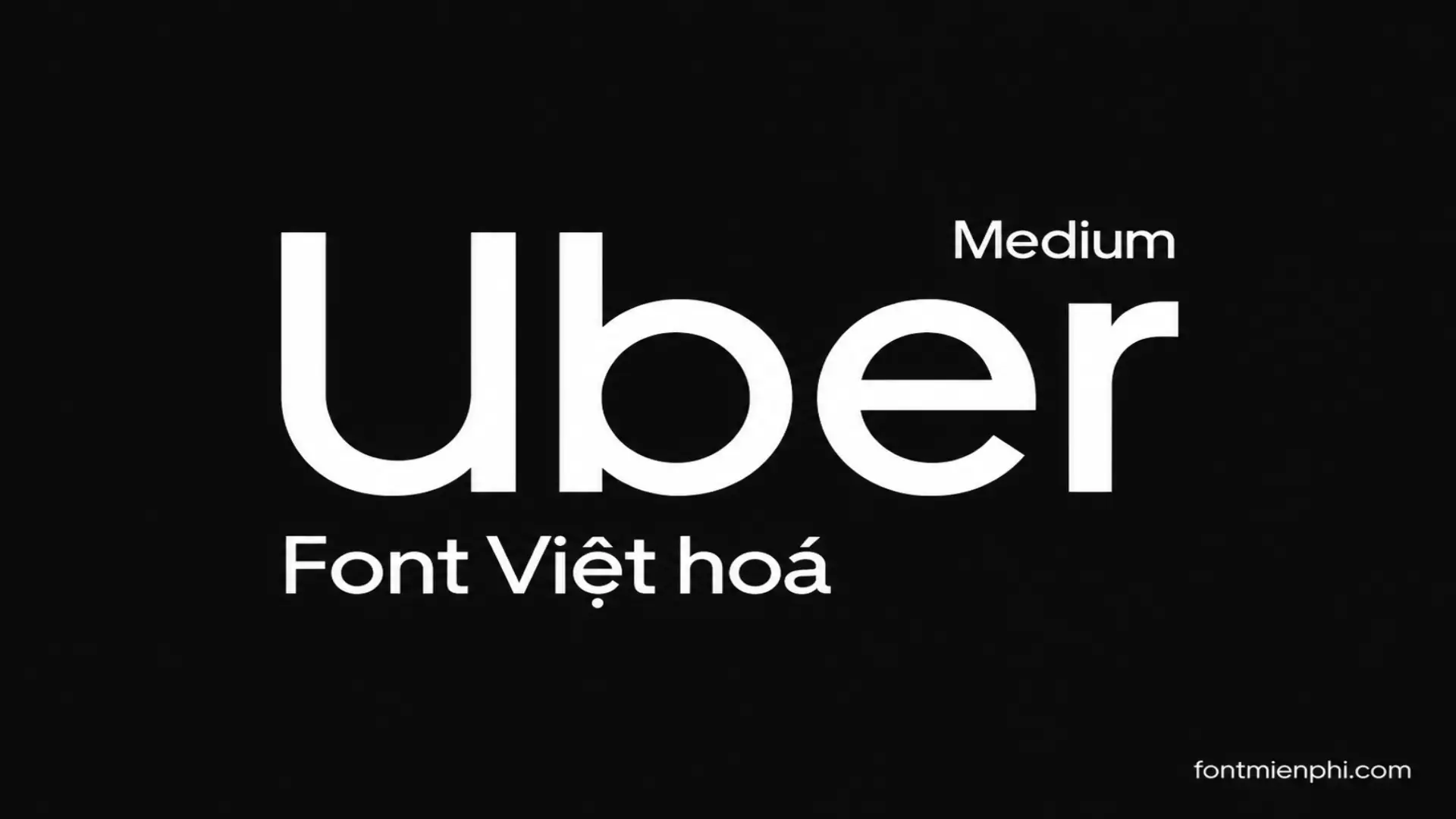
Tải Font Việt Hóa 1FTV VIP Uber Move Medium – Phông Chữ Hiện Đại, Chuyên Nghiệp
Nếu bạn đang tìm kiếm một phông chữ mang hơi thở đương đại, vừa tinh tế, sang trọng lại vô cùng chuyên nghiệp, thì Font Việt hóa 1FTV VIP Uber Move Medium chính là sự lựa chọn không thể bỏ qua. Đây hiện đang là một trong những phiên bản font chữ được cộng đồng Designer ưa chuộng nhất cho các dự án yêu cầu tính thẩm mỹ cao.
1. Giới thiệu về Font Việt hóa 1FTV VIP Uber Move Medium
Được phát triển dựa trên bộ phông chữ gốc đình đám của thương hiệu gọi xe công nghệ toàn cầu Uber, 1FTV VIP Uber Move Medium kế thừa trọn vẹn tinh thần cốt lõi: tối giản, hiện đại và hướng tới người dùng.
Phiên bản có độ dày Medium (trung bình) mang lại sự cân bằng hoàn hảo – không quá thanh mảnh gây khó nhìn, cũng không quá dày đặc gây cảm giác nặng nề. Đặc biệt, bản Việt hóa từ đội ngũ 1FTV đã được xử lý kỹ thuật tỉ mỉ, giúp các dấu câu tiếng Việt hiển thị mượt mà, đảm bảo sự rõ ràng và dễ đọc tuyệt đối trên mọi nền tảng.
2. Đặc điểm nổi bật của bộ Font 1FTV VIP Uber Move Medium
Phông chữ này mang trong mình những đặc tính xuất sắc để chinh phục mọi nhà thiết kế khó tính nhất:
Thiết kế tinh tế & chuyên nghiệp: Các đường nét được thiết kế bo góc nhẹ nhàng nhưng vẫn giữ được form dáng cứng cáp, mang lại cảm giác chỉn chu, đáng tin cậy.
Phong cách sang trọng & hiện đại: Rất phù hợp với xu hướng thiết kế tối giản (Minimalism) đang lên ngôi trong những năm gần đây.
Tối ưu hóa trải nghiệm đọc: Không gian giữa các chữ cái (kerning) được tính toán chuẩn xác, giúp người dùng dễ dàng tiếp nhận thông tin mà không bị mỏi mắt.
3. Ứng dụng thực tế hoàn hảo trong thiết kế
Với tính linh hoạt cao, Font Việt hóa 1FTV VIP Uber Move Medium có thể “cân” mượt mà nhiều hạng mục dự án khác nhau:
🎨 Thiết kế Đồ họa (Graphic Design)
Một phông chữ tuyệt vời để làm thiết kế bộ nhận diện thương hiệu (Branding), Logo, Namecard, Brochure, hay các Poster quảng cáo đòi hỏi sự sang trọng, đẳng cấp.
💻 Thiết kế Website (Web Design)
Với sự rõ ràng và tính thẩm mỹ cao, font chữ này cực kỳ lý tưởng để làm Typography cho các dự án thiết kế giao diện Website, đặc biệt là các trang web về công nghệ, doanh nghiệp, hoặc thương mại điện tử.
📱 Thiết kế Ứng dụng di động (UI/UX App)
Vì xuất thân là font chữ của một ứng dụng di động hàng đầu (Uber), Uber Move Medium hiển thị vô cùng sắc nét trên các màn hình kích thước nhỏ. Nó giúp giao diện UI/UX của app trở nên thân thiện và chuyên nghiệp hơn.
Kết luận: Font Việt hóa 1FTV VIP Uber Move Medium là một “trợ thủ đắc lực” không thể thiếu cho những dự án thiết kế cần sự giao thoa giữa tính chuyên nghiệp và thẩm mỹ hiện đại. Hãy tải về ngay hôm nay để mang đến một diện mạo mới mẻ và sang trọng cho các thiết kế của bạn!